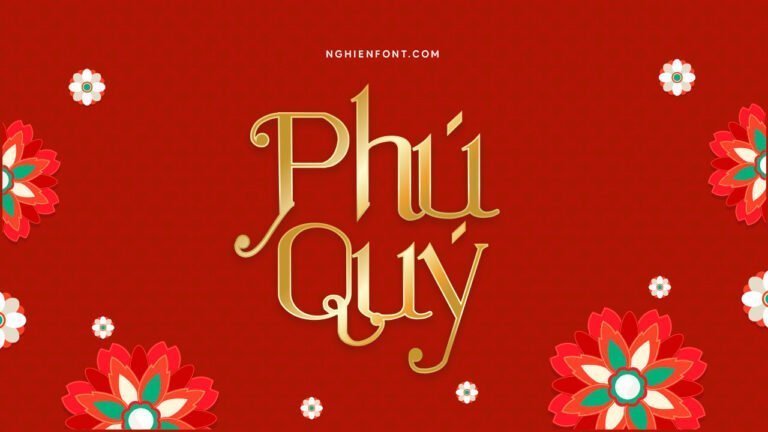
Font việt hóa LNTH Ratigk – Font siêu đẹp
Font viet hoa LNTH Ratigk
LNTH Ratigk là một kiểu font đẹp mắt với các nét chữ mềm mại ấn tượng phù hợp cho rất nhiều các thiết kế khác nhau như các dịp lễ Tết, Trung thu, đám cưới.
Các đường nét của chữ in hoa cứng cáp đi kèm với nó là các nét chữ in thường mềm mại mang đến khả năng sử dụng cho nhiều mục đích thiết kế khác nhau.
Font việt hóa LNTH Ratigk Preview
Font việt hóa LNTH Ratigk